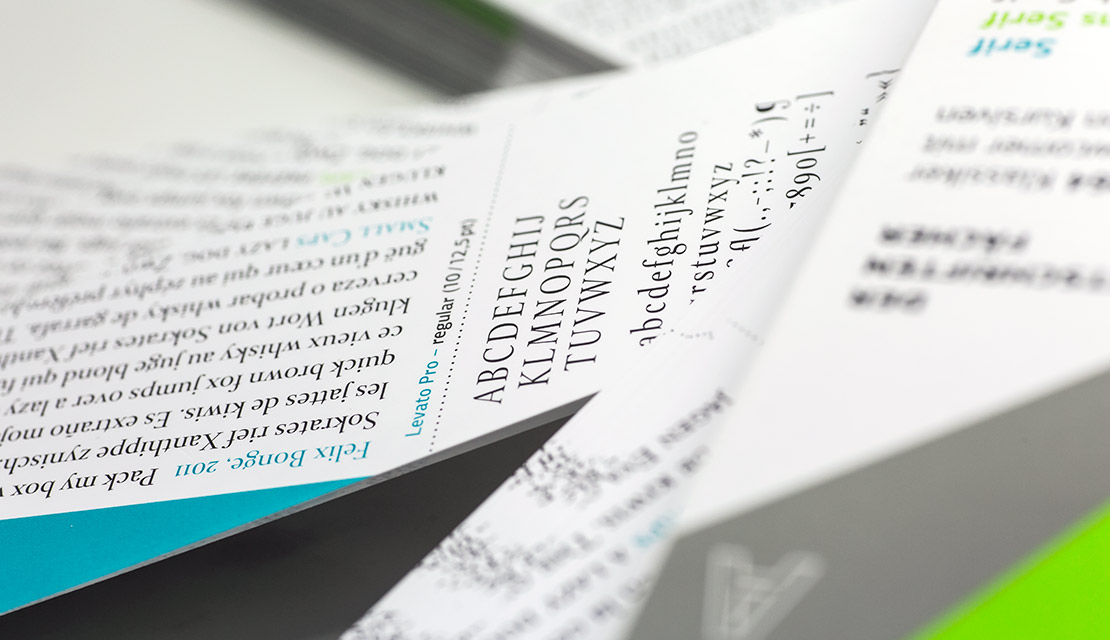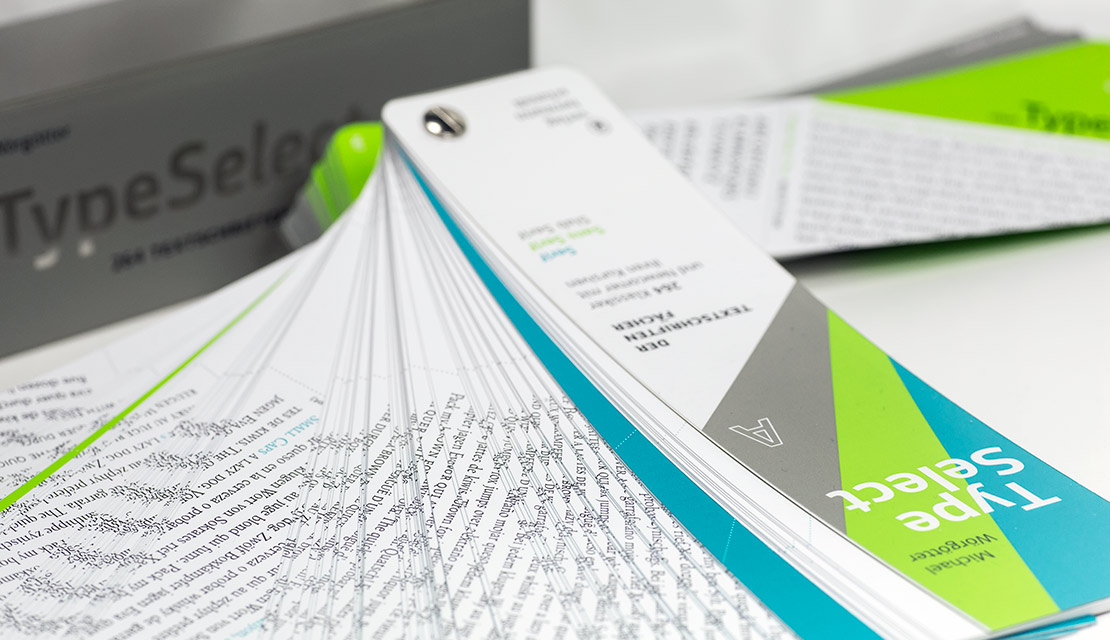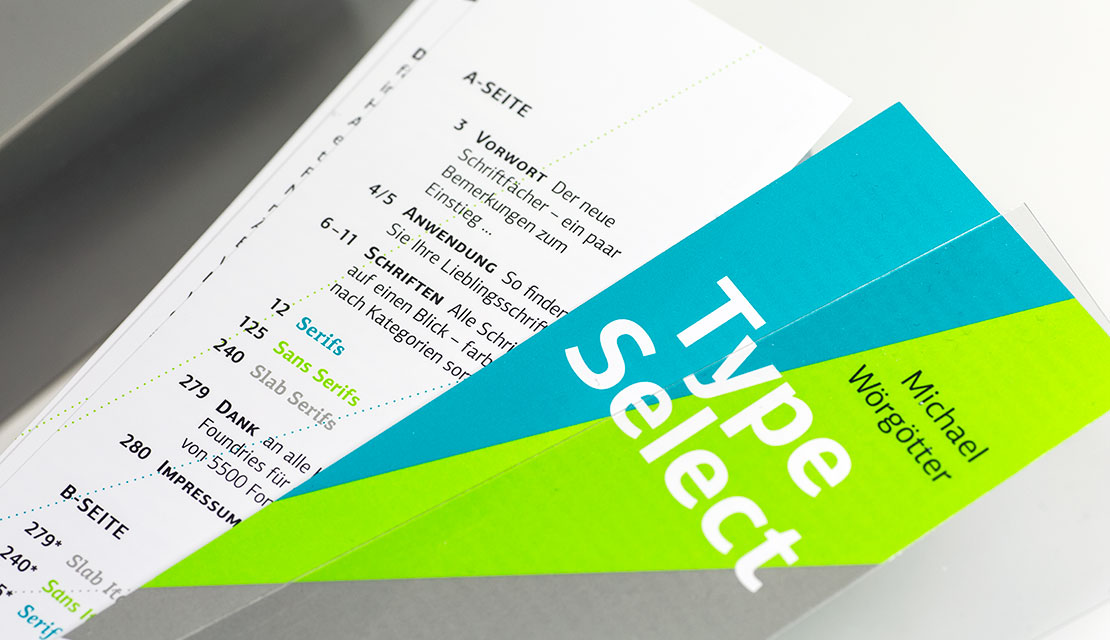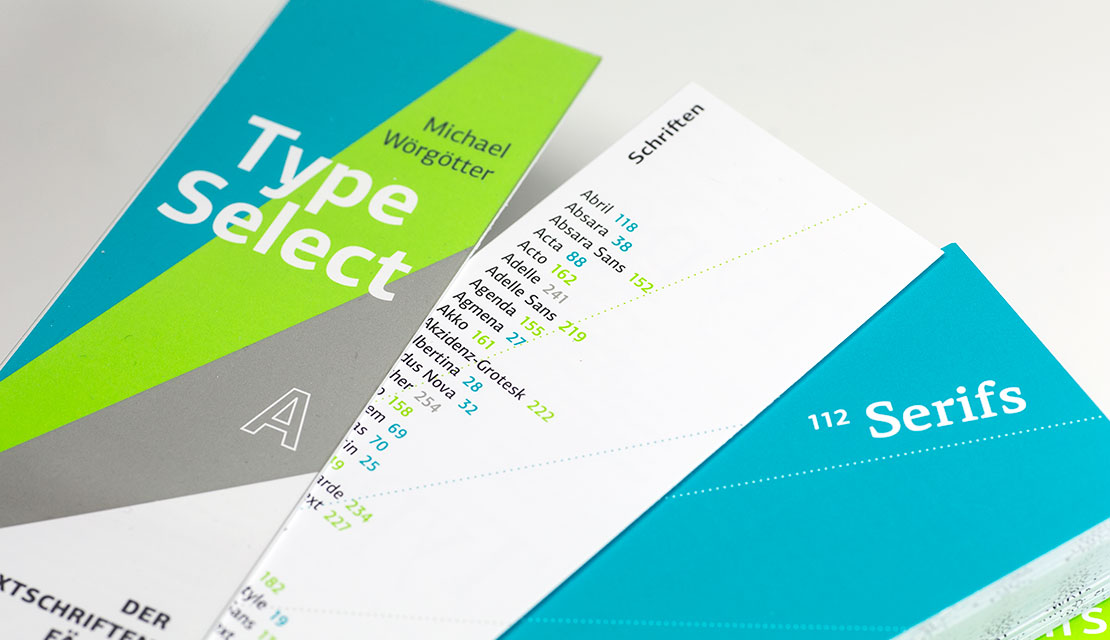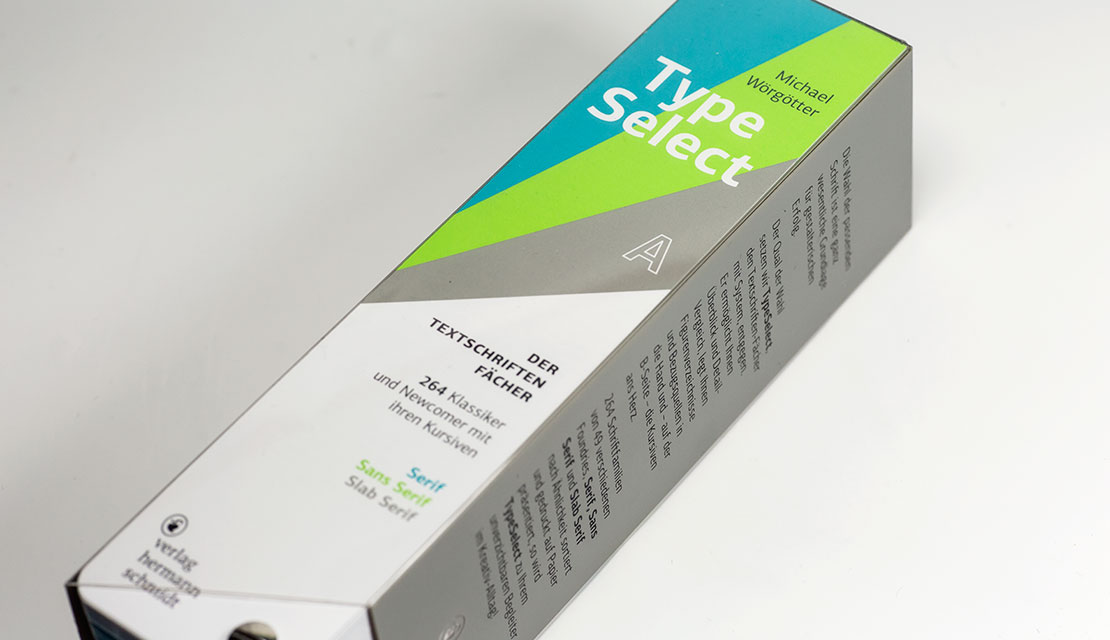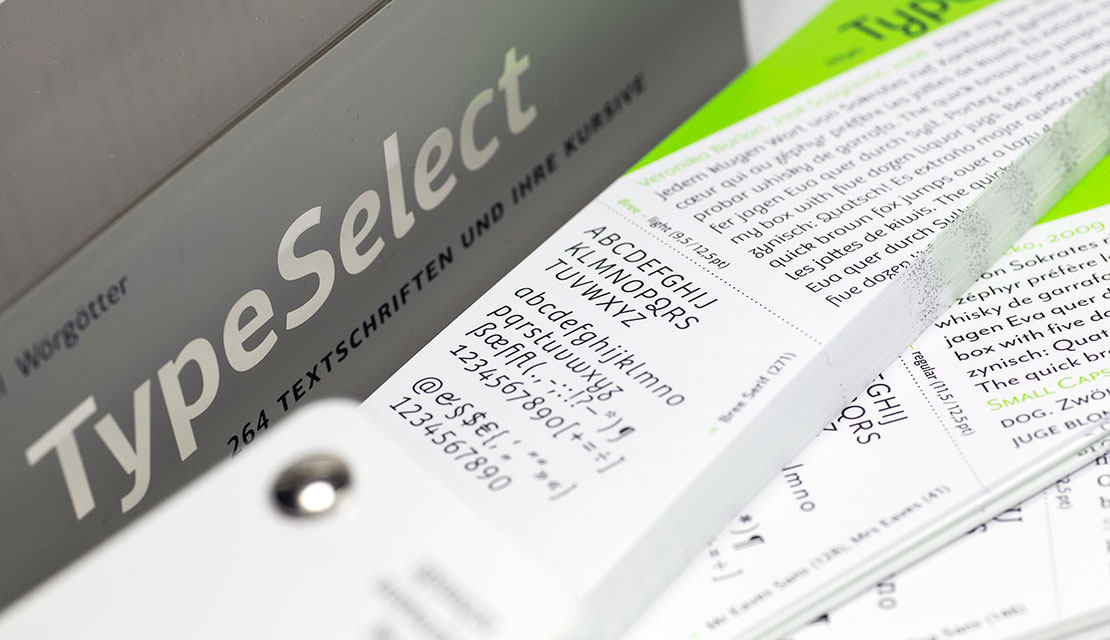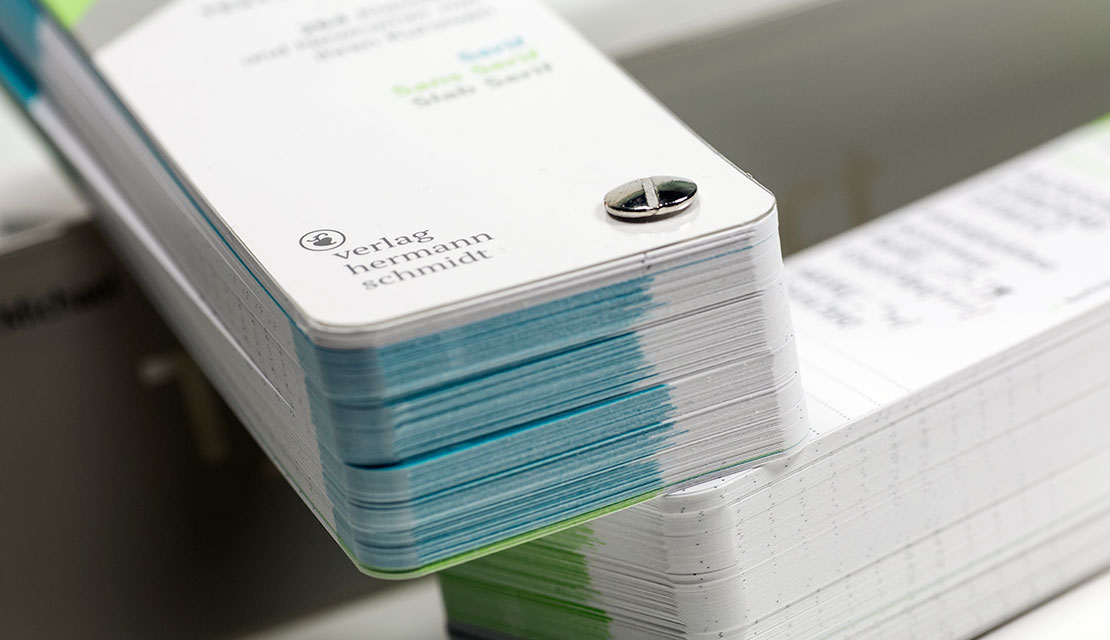
Schriftenfächer »TypeSelect«
Im Verlag Hermann Schmidt Mainz ist der Textschriften-Fächer »TypeSelect« erschienen. Er zeigt 264 Schriftfamilien von 49 verschiedenen Foundries – handlich auf Papier gebracht und nach Ähnlichkeit sortiert.
Das System funktioniert im Stile eines Farbfächers und erlaubt es, Schriften im Detail miteinander zu vergleichen. Die Fonts sind schräg aufs Blatt gestellt, so dass man beim Durchblättern den direkten Vergleich im Mengensatz hat. Ergänzend dazu gibt es Infos zu den verfügbaren Schnitten, dem Designer und den Bezugsmöglichkeiten. Die B-Seite zeigt die kursiven Schnitte der jeweiligen Schrift.
Michael Wörgötter hat sich bei seinem Fächer bewusst auf Fonts beschränkt, die für den Satz größerer Textmengen geeignet sind – und davon gibt es reichlich im Fächer.
Die Blätter sind sortiert nach Serif, Sans Serif und Slab Serif. Eine farbliche Unterteilung hilft, schnell zur passenden Schrift zu gelangen.
»TypeSelect« enthält 280 Blätter (Format 5 x 21 cm), die durch eine Buchschraube zusammengehalten werden. Mit dabei ist auch ein transparenter Schuber, der zur Aufbewahrung dient.